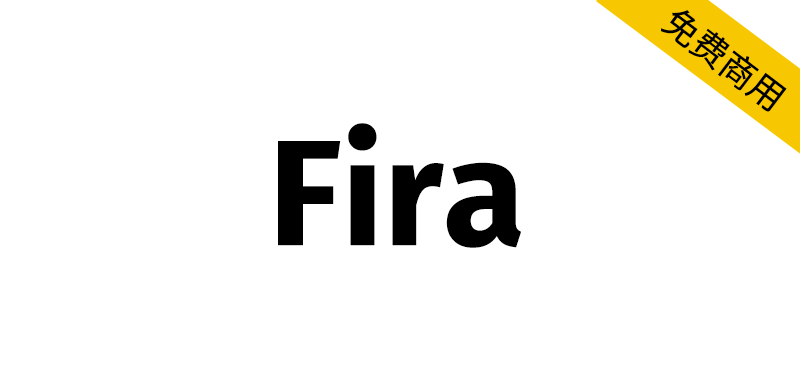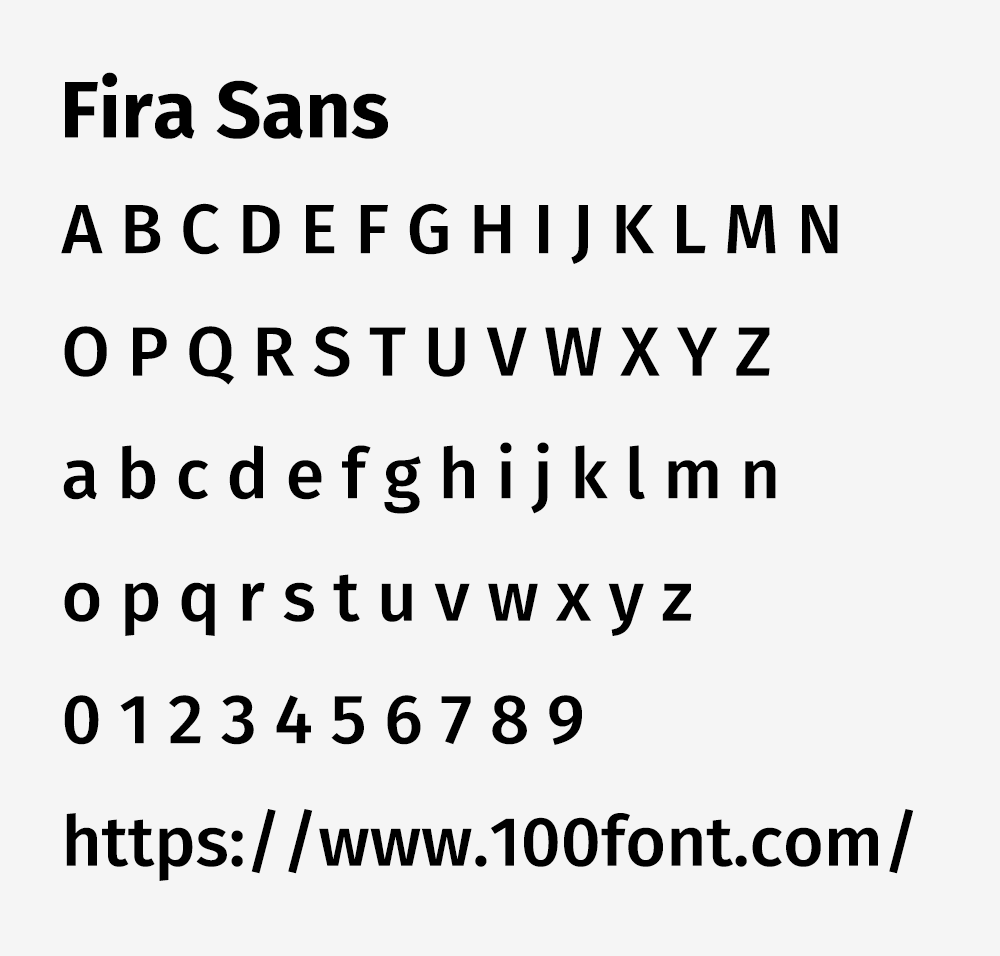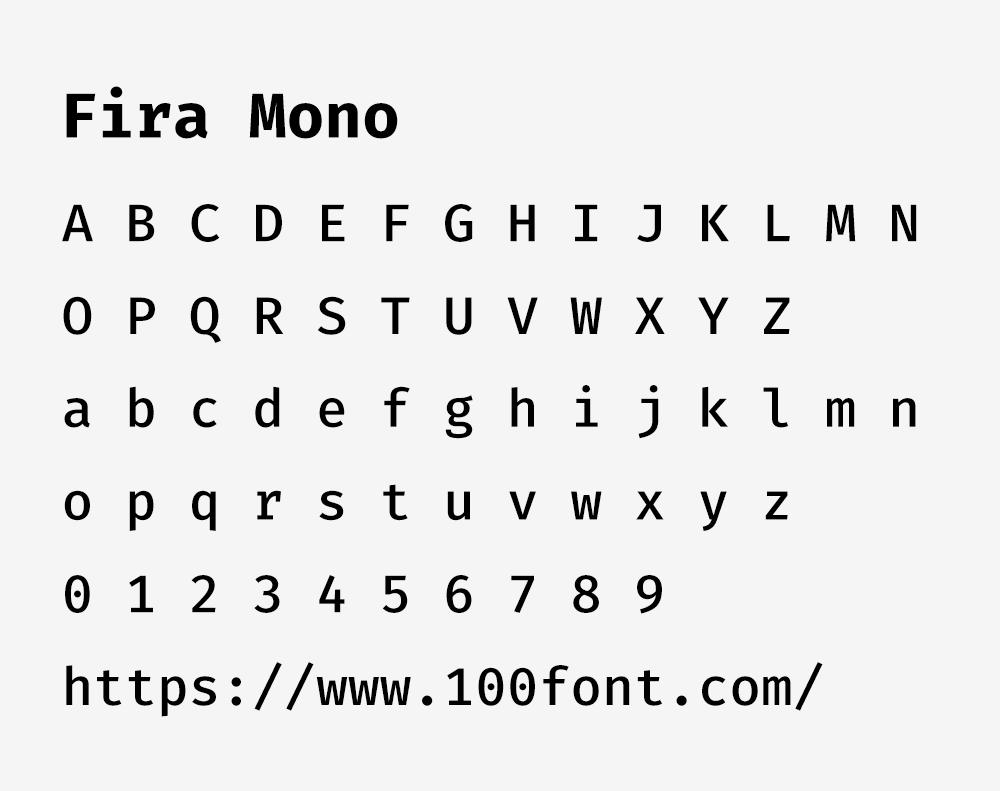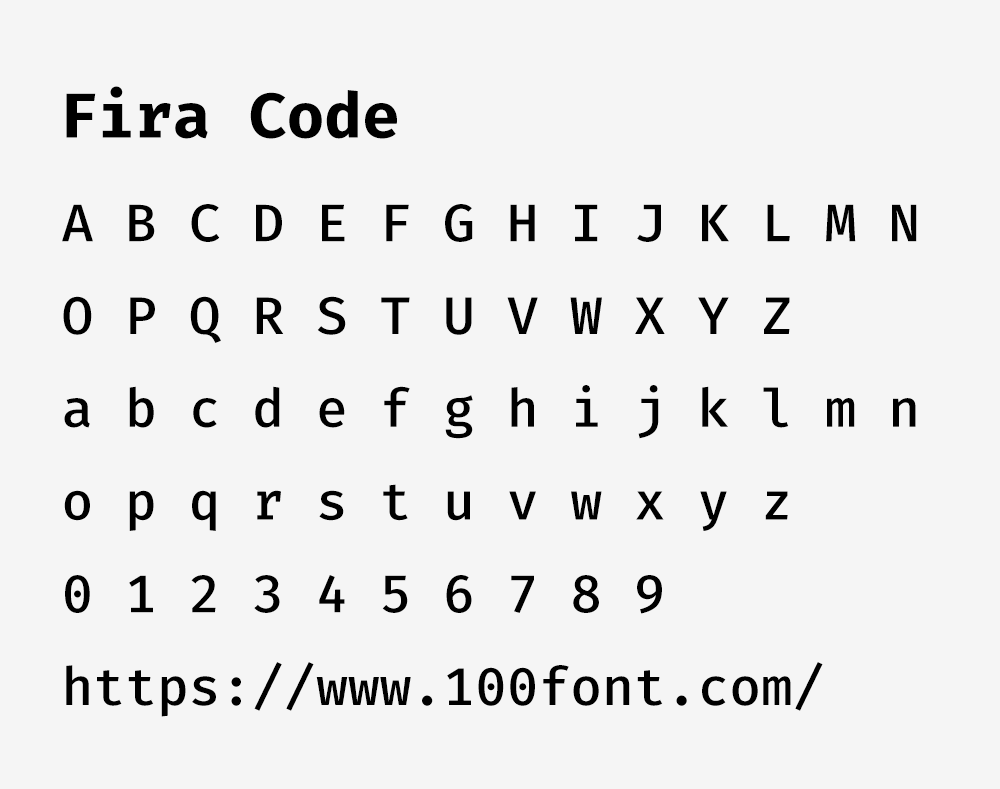
Fira(Fira Sans、Fira Mono、Fira Code)是一款现代感十足的无衬线字体家族,是由Mozilla 主持的开源字体项目,用于 Firefox OS,专为屏幕阅读和用户界面优化而生。其名称源自瑞典语中的"火"(Fira),寓意字体清晰锐利的视觉表现力。具备较好的连字特性,支持数学符号,字符集丰富,并配套由等宽字体。
○ 多语言支持 - 完整覆盖拉丁字母、希腊字母和西里尔字母
○字重丰富 - 支持超细体到超粗体多种字重
○等宽变体 - 提供 Fira Mono 等宽版本,适合编程使用
○先进排版特性- 支持 ligatures 、 small caps 等排版特性,确保在不同分辨率和大小的设备上都能保持良好的视觉效果
应用场景:网页设计、移动端UI、编程、代码编辑器等,该字体以其优异的可读性和中性美观的设计,成为众多科技公司首选的系统界面字体。